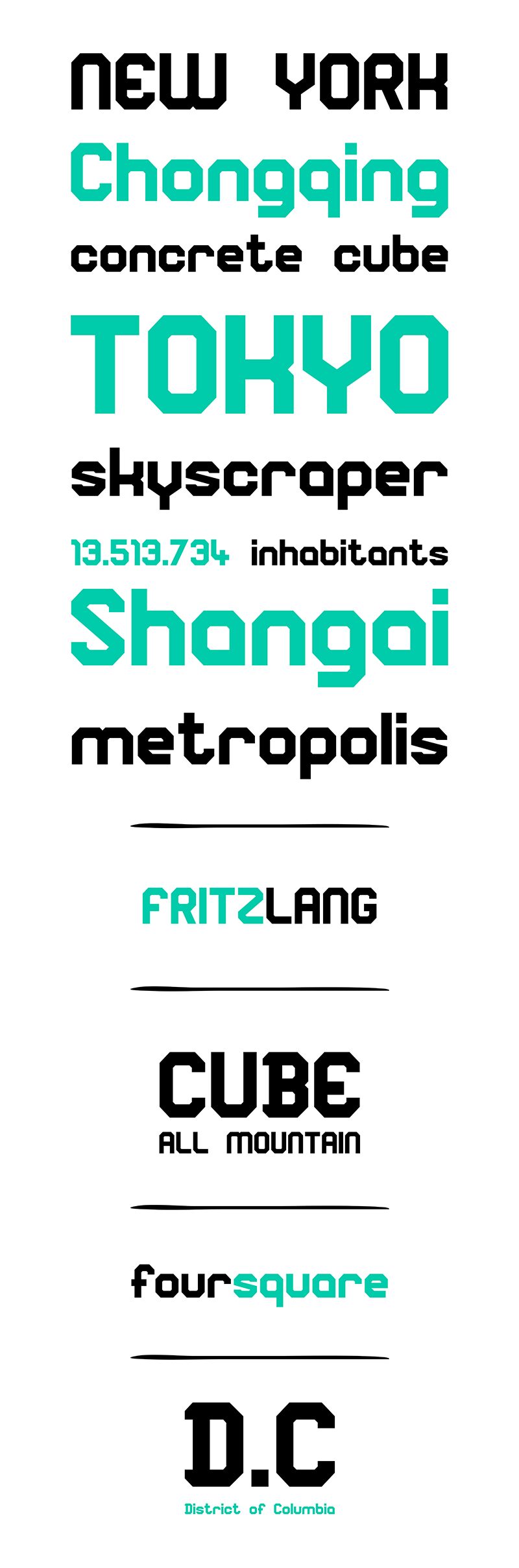
Square Block Regular to dzieło wyobraźni Andrei Cerboneschiego stworzone dla monocromo, które w swoim stylu techno łączy odważną i współczesną estetykę. Jako część rodziny Square Block, ten krój displayowy posiada półrozszerzoną szerokość, co poprawia czytelność, jednocześnie tworząc silny efekt wizualny. Wyrazista, pogrubiona waga podkreśla jego obecność, sprawiając, że każdy znak zajmuje swoje miejsce z autorytetem i charakterem.
Geometryczna precyzja i czyste linie Square Block Regular budzą skojarzenia z nowoczesnością i wyrafinowaniem, co czyni go doskonałym wyborem do brandingu, interfejsów cyfrowych czy wszelkich projektów, w których liczy się innowacja i siła. Jego estetyczny urok tkwi w harmonii między ostrymi kątami a zbalansowanymi proporcjami – idealny dla projektantów chcących wprowadzić elegancki, techniczny klimat do swoich prac.
Niezależnie od tego, czy użyjesz go w nagłówkach, czy jako akcentu w logotypach, Square Block Regular wyróżnia się umiejętnością połączenia funkcjonalności z designem o dużym wpływie, wynosząc kreatywne projekty na czoło współczesnej kultury wizualnej.
Square Block to dekoracyjny krój pisma inspirowany architekturą przedmieść Florencji.
Monospaced krój displayowy o masywnej strukturze, odpowiedni do przekazów o zdecydowanym charakterze.
Przydatny w reklamach, na billboardach, w logotypach i nagłówkach.